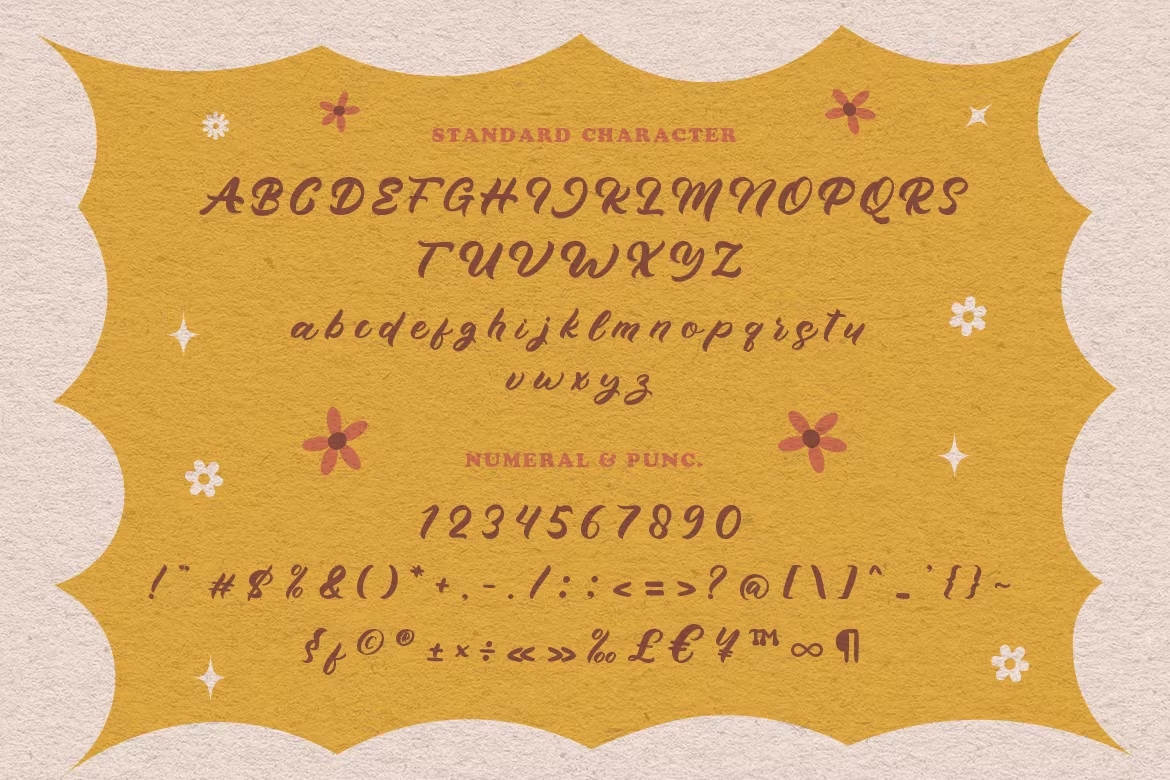
Willydope Font
Présentation d’une nouvelle police de notre collection de scripts appelée Willydope. Cette police dessinée à la main est réalisée dans un style numérique dessiné à la main dans un look scripté élégant. Cette police convient à la conception de logos, aux médias sociaux, aux titres de films, aux titres de livres, aux textes courts, même aux lettres de texte longues, et convient à votre police de texte secondaire avec sans ou empattement.
Majuscules et minuscules standard
Chiffre et ponctuation
Multilingue : ä ö ü Ä Ö Ü ß ¿ ¡
Alternance et Ligature